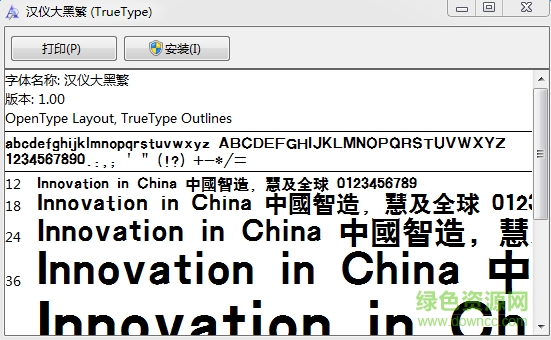
hyb2gf字體是漢儀大黑繁體字體的簡(jiǎn)寫名稱。該字體構(gòu)體莊重,飽滿大氣,應(yīng)用廣泛,用作廣告字體、美術(shù)字體或海報(bào)字體都可以!綠色資源網(wǎng)還有超多個(gè)性字體等你下載!
漢儀大黑簡(jiǎn)字體樸素大方、粗重平穩(wěn)、橫豎比例一致、結(jié)構(gòu)嚴(yán)謹(jǐn),非常引人注目,常用作印刷中穩(wěn)重、醒目的標(biāo)題字。